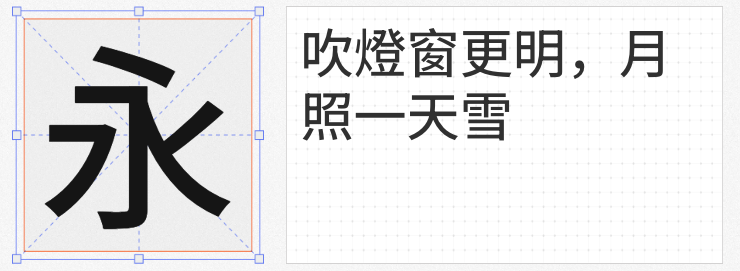
在视觉设计领域,黑体因其简洁有力的视觉语言成为品牌传播、广告创意、数字媒体的核心字体类型。本文精选四款免费商用黑体,从现代设计到文化传承,满足多元场景需求。
作为锐字工坊推出的免费商用字体,锐字潮牌真言简2.0 超粗以“笔触浑厚、结构张力”为核心设计语言。其笔画采用直角与圆角的错落搭配,横竖笔画粗细对比强烈却不失平衡,转折处圆角处理弱化锐利感,形成“刚柔并济”的独特风格。例如在海报标题中,超粗字重能瞬间抓住视觉焦点,而笔画中的留白设计又避免厚重感,适合科技、运动、潮流类品牌表达力量与活力。该字体免费开放下载,支持商业用途,是性价比极高的设计利器。
由Adobe与Google联合开发的思源黑体,是开源字体领域的里程碑之作。其SC Heavy版本以“重心低、中宫开阔”为特点,笔画粗细均匀,字形端庄稳重,尤其适合长文本阅读与屏幕显示。作为泛CJK字体家族,它覆盖简体中文、繁体中文、日文、韩文,且支持7种字重与可变字重技术,设计师可通过软件无级调节粗细,适配从标题到正文的多元需求。例如在跨国品牌手册中,思源黑体能统一多语言排版,展现专业性与包容性。
阿里巴巴普惠体3 115 Black字重以“瘦长、高重心”为设计语言,笔画简化(如省略标题字出脚部分)与几何化处理,赋予字体“轻盈、现代”的视觉感受。其灵感源自20岁少年的精气神,适合互联网、电商、文创类品牌传递年轻化态度。例如在APP界面中,Black字重能提升信息层级,而瘦长字形则优化屏幕空间利用率,兼顾美观与功能性。
基于思源黑体改造的源古黑体,是首款严格遵循《古籍印刷通用字规范》的免费商用字体。其字形取自《辞源》与古籍数字化资源,笔画严谨复刻宋体特征,同时扩展B区字符(如生僻字、异体字),填补古籍排版领域的空白。例如在文化展览、学术出版中,源古黑体能精准还原历史文献的视觉风貌,让传统文字以数字化形式延续生命力。